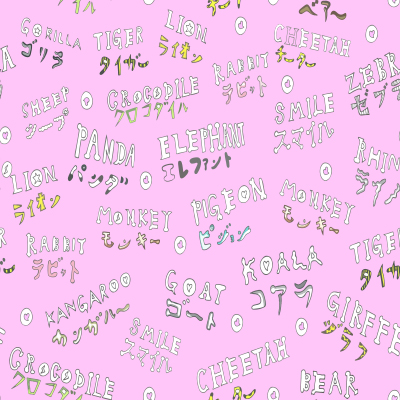
ぼくらの名前は PINK
君の名前、素敵だね。あなたの色こそ、素敵!そのちがいは、「わたし」を表す。そのちがいで、わたしはわたしを表現できる。表現の場としてわたしたちを受け入れてくれる渋谷で生まれるハートフルなイメージを表現しました。(井上 智絵)
丁寧に鉛筆で下描きをして、緻密なレタリングを完成させました。動物たちの名前に混じって「スマイル」とあるのが、普段は口数の少ない作者の、粋なユーモアです。(工房ぱれっと)